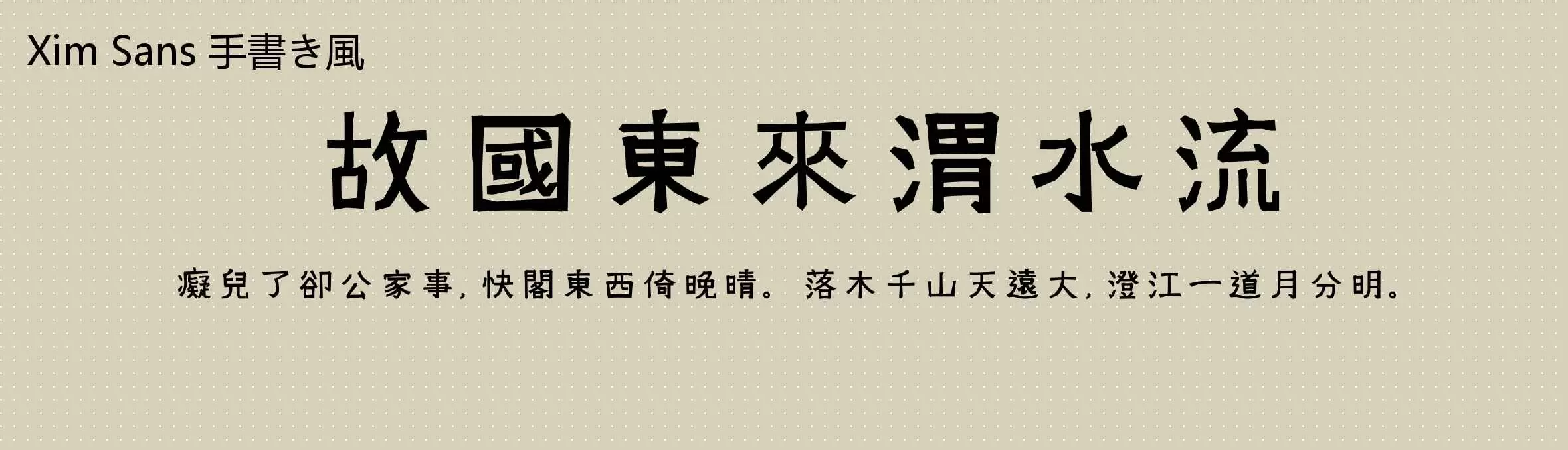
《Xim Sans手写体》是一种中文手写字体,它具有简洁清晰、自然流畅的特点。字体的笔画饱满且有力,又不失柔和轻盈的感觉。字母之间的间距适中,适合各种场景的应用,包括海报设计、书籍排版、电子屏幕等等。《Xim Sans手写体》是一种高品质的字体,非常适合用来表达个性、创意及独特的视觉体验。无论是个人或商业用途,都可以通过使用这种字体来增加品牌或作品的独特性。